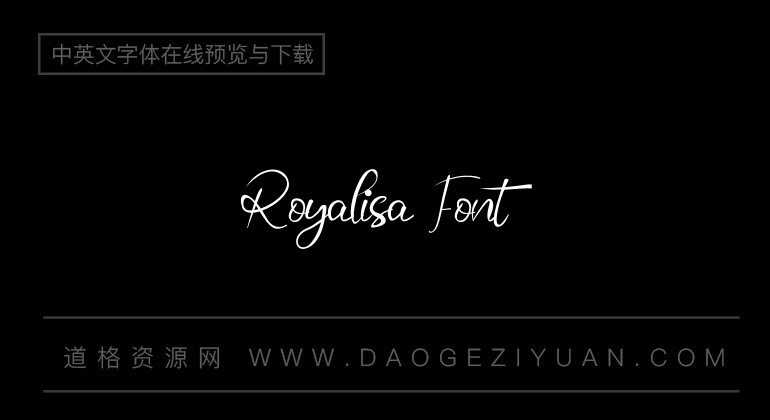
Royalisa Font 是一种现代化的手写风格字体,它具有很高的可读性和美观的视觉效果。该字体包含了大写字母、小写字母、数字、标点符号以及特殊符号等多种字符,可以用于各种设计项目,例如海报、名片、标志等等。 Royalisa Font 字体具有优美的笔画和流畅的曲线,让它看起来既现代又优雅,非常适合在各种文本上使用。该字体还包括一些额外的特性,例如弯曲的线条和斜线,这些都可以使其更加独特和引人注目。 总之,Royalisa Font 是一款多用途的字体,适用于许多场合,无论是印刷品还是数字设计,都可以很好地展现其独特的美感和实用性。内容介绍
Royalisa Font是一款非常不错的手写艺术字体,具有很好的视觉感,适合于文化类的宣传设计、商业类品牌的广告和产品包装设计以及个性化文字排版等较多场景。